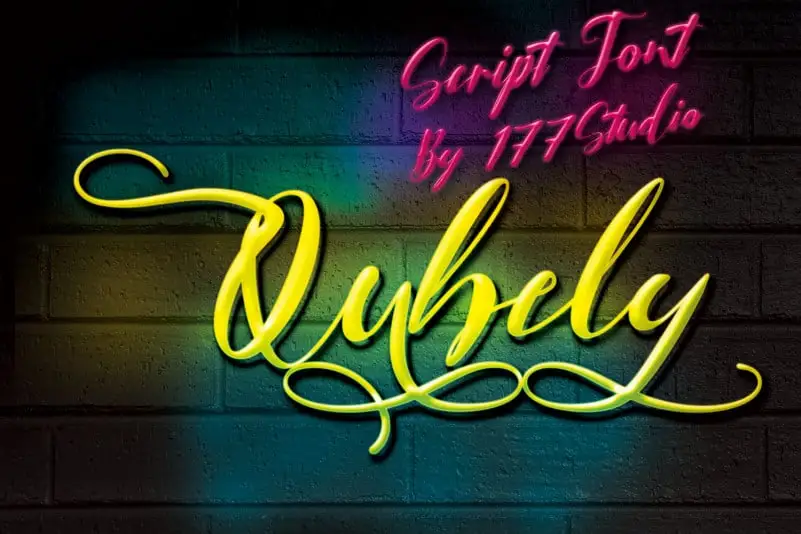
Qubely Script Font – Download Grátis
Qubely Script Font é uma elegante fonte script que traz consigo um toque descontraído e incrivelmente divertido. Com seu acréscimo de energia, este tipo permite criar layouts tipográficos cuidadosamente feitos instantaneamente. Seja para estaçãoários, logos ou qualquer projeto onde você precisa de uma letra delicada com um aspecto autêntico de arte manual, Qubely Script Font é o ideal. Como mencionado na descrição original em inglês, esta fonte é perfeitamente adaptada a estilos modernos e hand-made, permitindo que seu design atinja um sentido authentico, trazendo uma personalidade única a qualquer projeto. Se você está procurando por uma fonte que combine elegância com um leve toque de diversão, Qubely Script Font será uma excelente escolha para tornar seus designs mais autênticos e únicos.